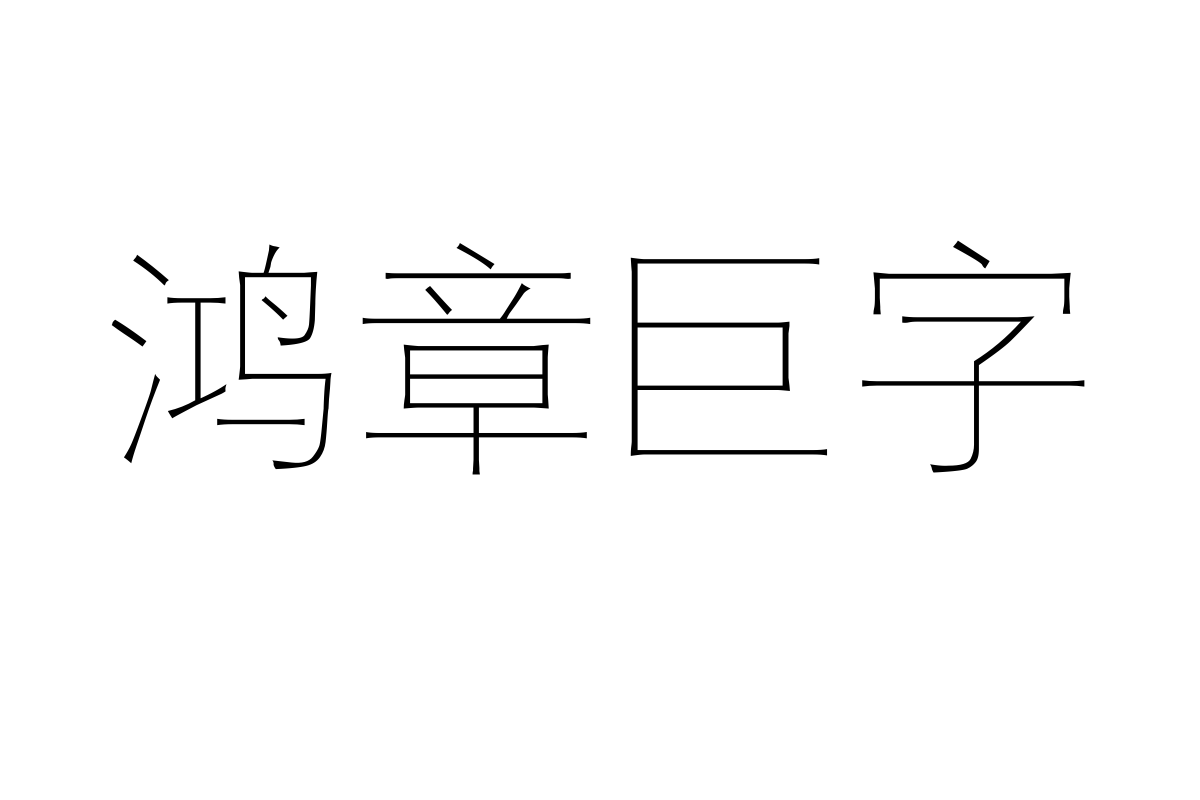
汉仪特细等线简是一款由汉仪公司设计开发的中文字体。这款字体的特点是线条细腻,字形规整,适用于需要精细排版的场合。它的特点包括:
1. 线条细腻:汉仪特细等线简的线条非常细腻,可以很好地表现出细节和纹理,使文字更加生动。
2. 字形规整:这款字体的字形规整,没有多余的装饰,给人一种简洁、大方的感觉。
3. 适用范围广:由于其线条细腻,字形规整,因此适用于需要精细排版的场合,如杂志、报纸、广告、书籍等。